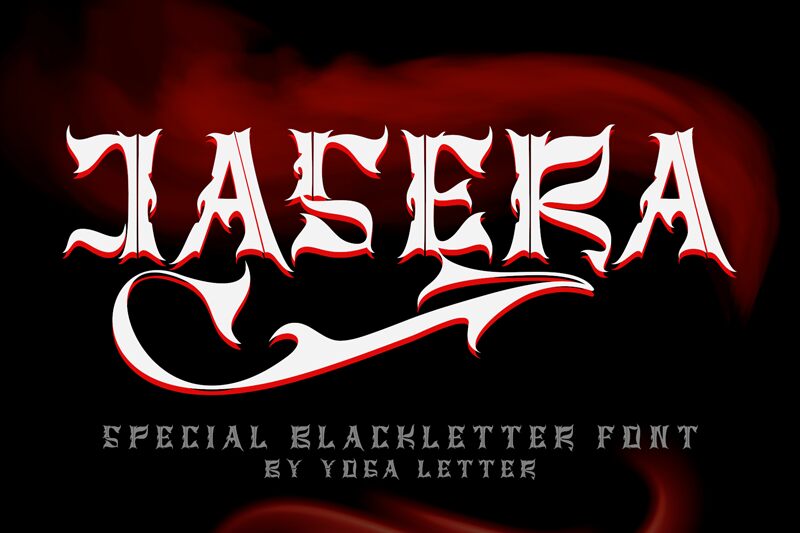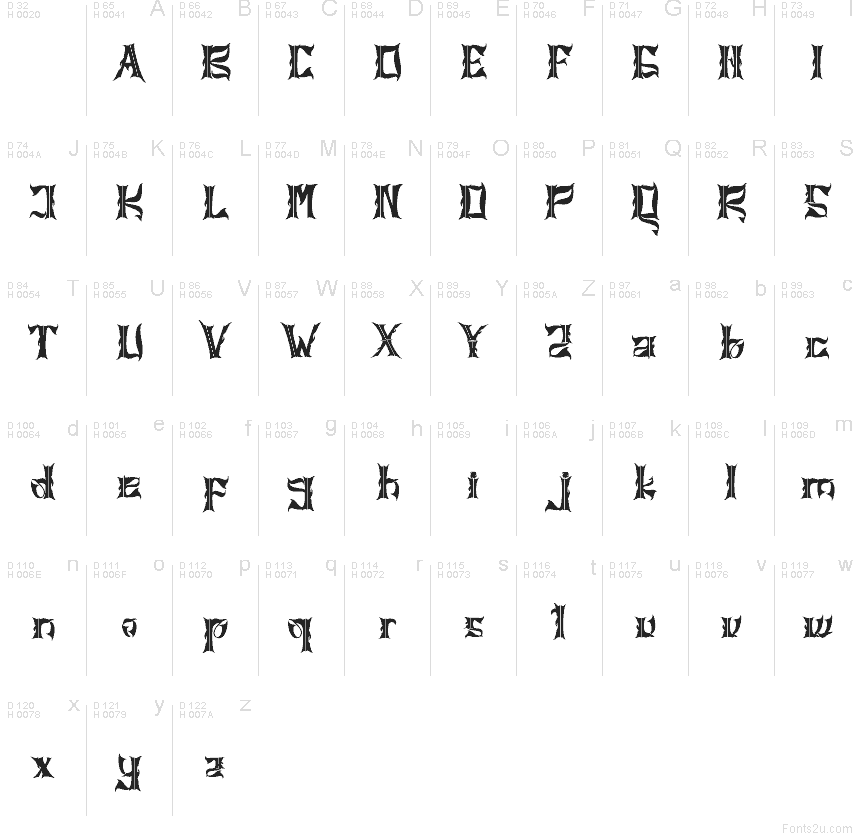
Jasera
La police Jasera de Yoga Letter est une police gothique gratuite aux empattements acérés et crochus. Ses découpes internes fluides confèrent aux caractères une esthétique sculptée, presque calligraphique. Le dessin mélange des verticales étroites et des jonctions incurvées et pointues, créant un rythme ornemental sombre qui semble façonné sur mesure plutôt que purement géométrique.
Jasera est une police gratuite idéale pour les logos aux influences métal, les visuels de groupes, les lettrages de tatouage, les titres d'affiches, les jeux vidéo et les emballages horrifiques. Ses détails découpés et ses formes dramatiques conviennent parfaitement aux badges, aux pochettes d'albums et aux phrases décoratives courtes où la typographie doit être l'élément central du design.